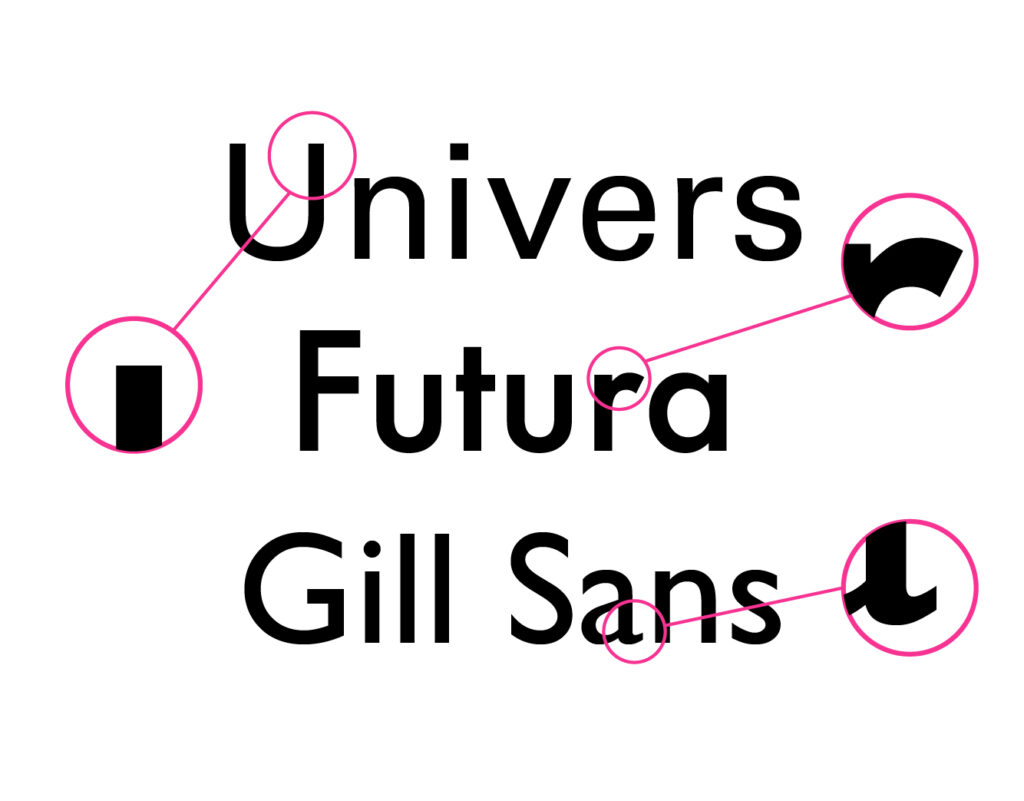
SANSERIF
Es el nombre que se le da a aquellas tipografías que carecen de terminaciones o remates.
Según la clasificación de la Asociación Tipográfica Internacional (ATypI) se dividen a su vez en cuatro subgrupos: Grotescas, Neogrotescas, Geométricas y Humanísticas.
SIN.: Palo seco, lineales.